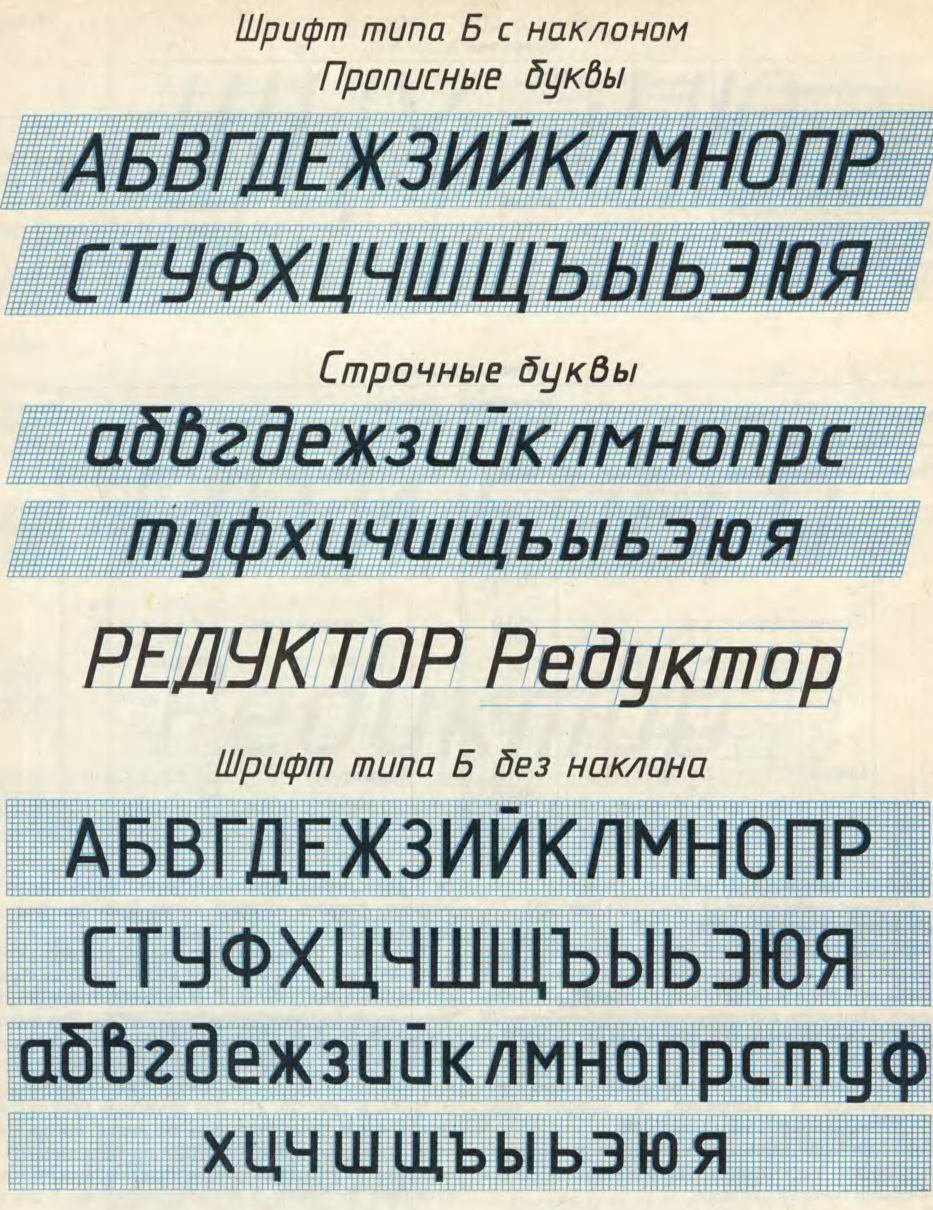
Шрифты чертежные. Чертежи, схемы и другие конструкторские документы содержат необходимые надписи: название изделий, размеры
Чертежи, схемы и другие конструкторские документы содержат необходимые надписи: название изделий, размеры, данные о материале, технические требования, спецификации. Если надписи сделаны небрежно, то при изготовлении деталей по таким чертежам возможны ошибки. Типы и размеры шрифтов, цифр, знаков и т.д. устанавливает ГОСТ 2.304-81. Размер шрифта h – величина, определенная высотой прописных букв в миллиметрах. Толщина линии шрифта d зависит от типа и высоты шрифта ГОСТ устанавливает следующие размеры шрифта: (1,8); 2,5; 3,5; 5; 7; 10; 14; 20; 28; 40. Стандартом установлены 2 типа шpифтов: тип А и тип Б, каждый из котоpых можно выполнить или без наклона, или с наклоном 75 гpадусов к основанию стpоки. В учебной практике предпочтительнее применять шрифт типа Б с наклоном 75 градусов.
Рисунок7 Шpифты выполняют пpи помощи вспомогательной сетки, обpазованной тонкими линиями, в котоpую вписывают буквы. Шаг линий сетки опpеделяется в зависимости от толщины линий шpифта d (рисунок 8).
Рисунок 8
Таблица 5 – Размеры шрифта
Начертание шрифта типа Б приведено на рисунке 9.
Рисунок 9
Написание цифр и конструкция некоторых знаков дана на рисунке 10.
Рисунок 10 Пример оформления надписей (рисунок 11)
Рисунок 11 Для выполнения упражнения по написанию букв и цифр следует разметку сетки выполнять упрощенно (рисунок 12).
Рисунок 12
Таблица 6 – Размеры букв и цифр в мм.